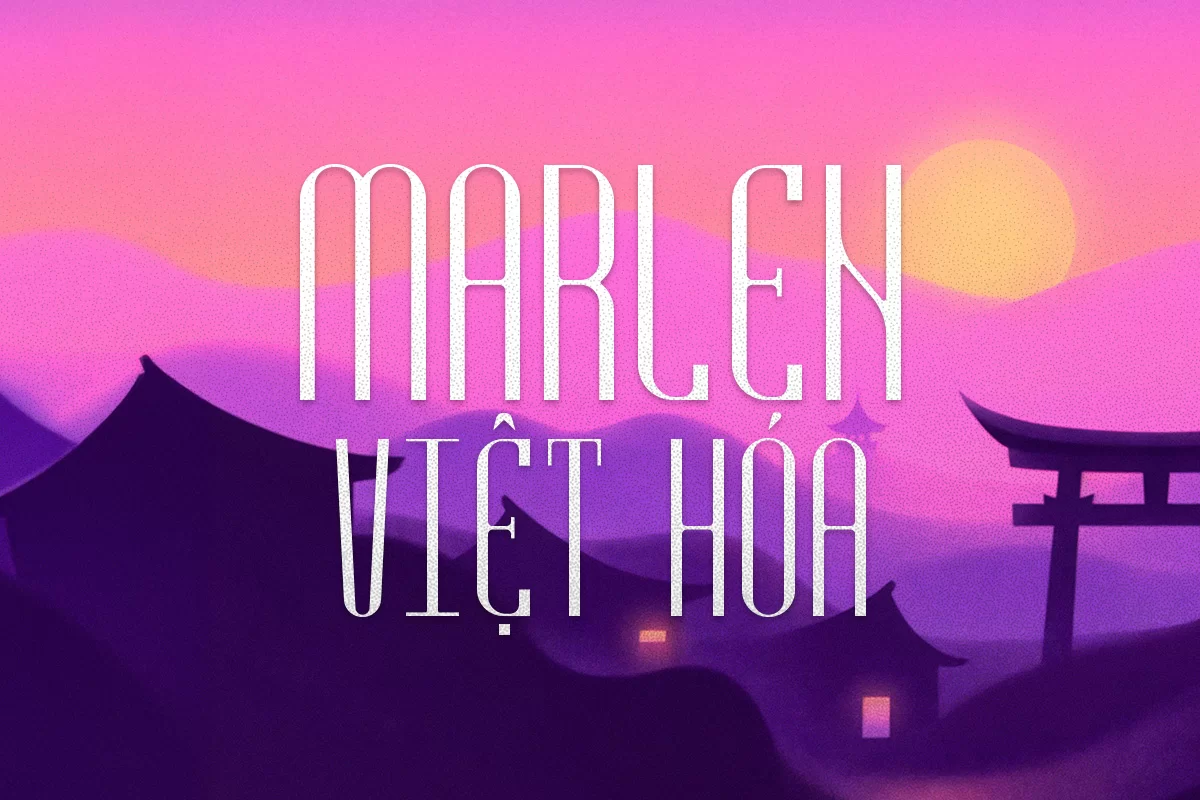
Marlen Việt Hóa là một kiểu chữ sans-serif hiện đại mang đậm phong cách thời trang và sang trọng. Với các đường nét cao, thanh mảnh và khoảng cách chữ rộng, Marlen tạo cảm giác thanh lịch, phù hợp với các thiết kế cao cấp như thương hiệu thời trang, mỹ phẩm, bìa tạp chí hay poster sự kiện. Font nổi bật nhờ kiểu dáng chữ cái kéo dài độc đáo nhưng vẫn đảm bảo khả năng đọc tốt ở kích thước lớn. Phiên bản Việt hóa được tối ưu đầy đủ dấu tiếng Việt, đảm bảo sử dụng mượt mà trong thiết kế nội địa. Marlen không chỉ là một font chữ mà còn là một tuyên ngôn thẩm mỹ – lý tưởng cho những ai đang tìm kiếm sự khác biệt tinh tế trong dự án của mình. Đây là lựa chọn hoàn hảo cho nhà thiết kế đang cần điểm nhấn đẳng cấp và hiện đại.